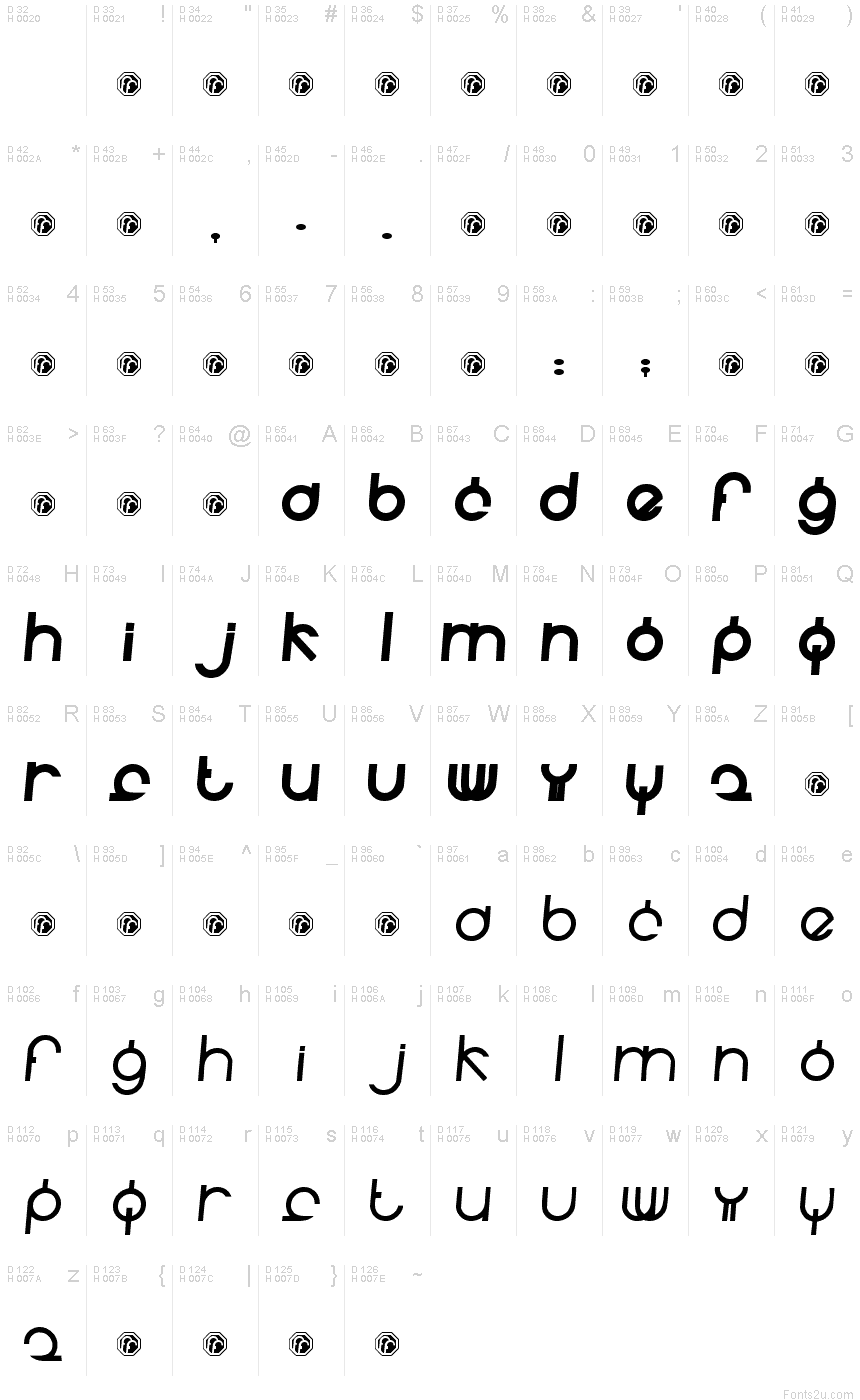
Fidelle od Font"a"licious Fonts to darmowy, nowoczesny font displayowy o wyrazistym, niemal kinetycznym rytmie. Jego masywne, zaokrąglone formy ścierają się z wysokimi, pochylonymi liniami, tworząc wrażenie ruchu nawet w pojedynczym słowie. Litery sprawiają wrażenie rzeźbionych, a nie rysowanych – to grube, atramentowe pasma, które przecinają linię i łączą się ze sobą niczym elementy spersonalizowanego logo.
Fidelle nadaje nagłówkom charakteru, idealnie sprawdzając się na plakatach muzycznych, klubowych ulotkach, logotypach marek, metkach odzieżowych, opakowaniach czy w grafice do mediów społecznościowych, która potrzebuje pazura. Wąskie światła i ciężkie kształty najlepiej prezentują się w dużych rozmiarach, dlatego niech ten darmowy font dominuje w projekcie, a w mniejszych tekstach zestaw go z czystym krojem bezszeryfowym, aby całość pozostała czytelna i ostra.